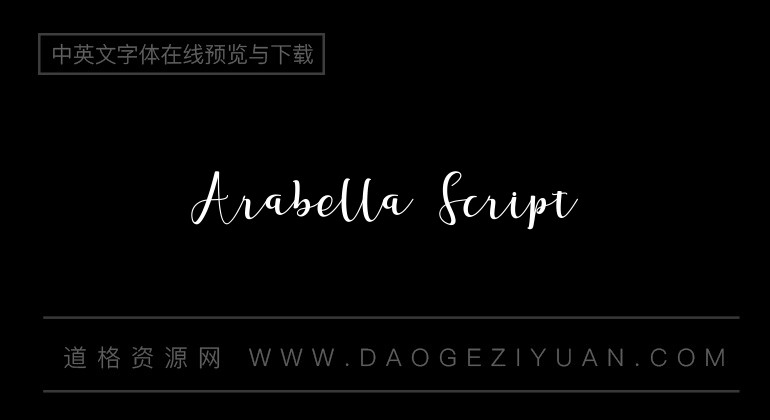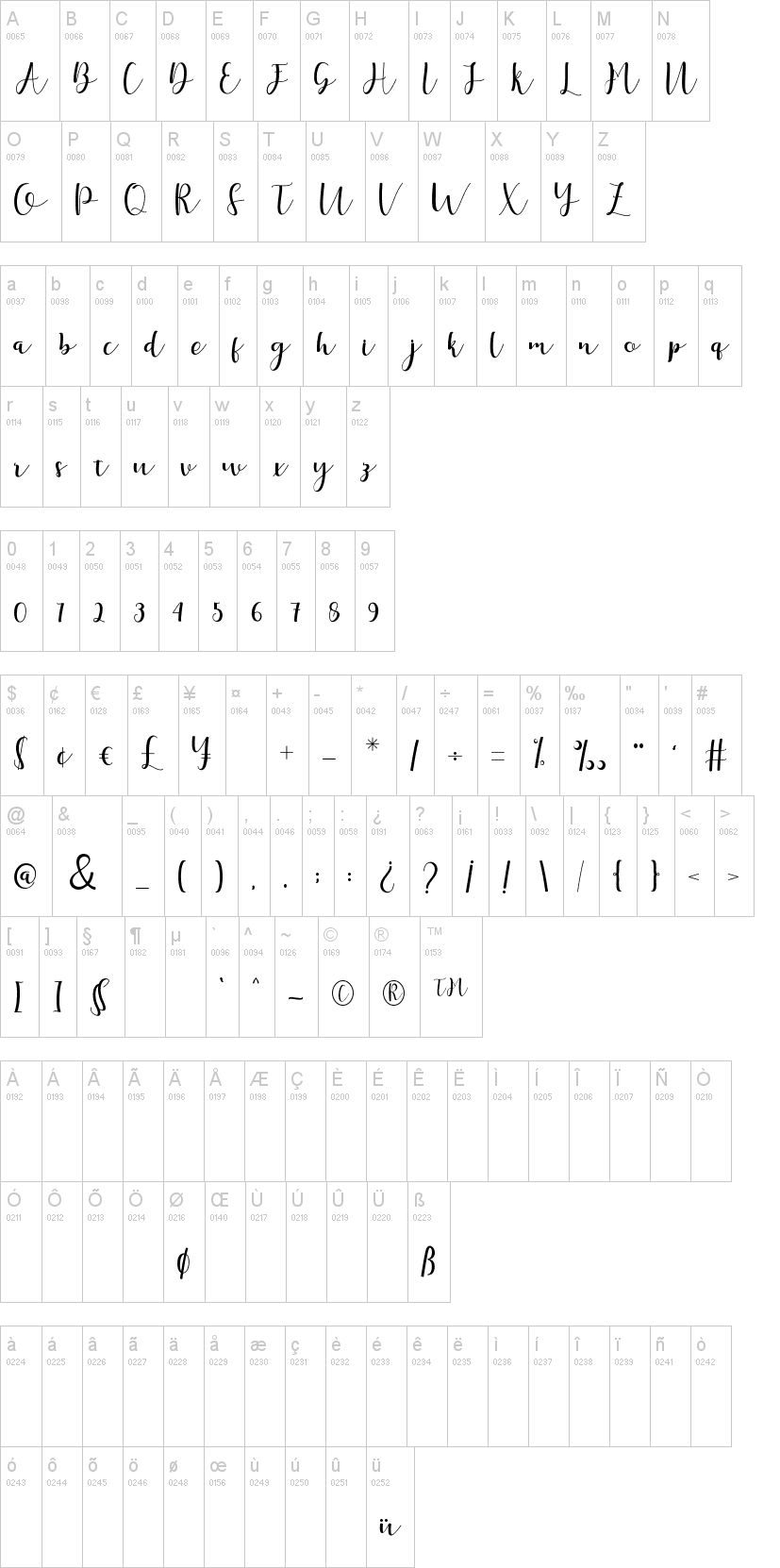
? Arabella Script 是一款精美的手写体字体,它具有优雅的曲线和流畅的字形,可以用于各种印刷品、海报、T恤、婚礼邀请函、标志和许多其他应用。它的特点是每个字母都有一种独特的设计,它们看起来既精致又优雅,可以让你的设计看起来更加独特而精致。内容介绍
Arabella Script是一款非常不错的手写艺术字体,具有很好的视觉感,适合于文化类的宣传设计、商业类品牌的广告和产品包装设计以及个性化文字排版等较多场景。